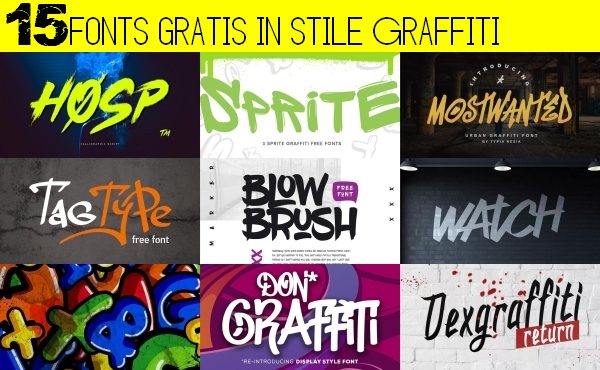
Se siete alla ricerca di un fonts particolare per il design di un poster, una copertina o un lavoro di grafica in generale, dovreste prendere in considerazione lo stile graffiti.
Questo tipo di font presentano spesso un design unico e un aspetto che attira l'attenzione.
15 fonts gratis in stile Graffiti